TP明朝で広がるWebデザイン
Webデザインを軸に、ロゴ、名刺、パンフレットなどのグラフィックを一貫して手がけるデザイン事務所THROUGH代表の大津厳氏。2015年春に渋谷ヒカリエで開催されたデザイン展『NIPPONの47人』では、岐阜県代表に選ばれ、そのシンプルで洗練された作品が注目を浴びました。以前からAXIS Fontを愛用していた大津氏は、デジタルディスプレイでの利用を前提として開発されたTP明朝にいち早く着目し、さまざまな企業のためのグラフィックで活用しています。
「2014年の初頭に、タイププロジェクトからTP明朝という新しい明朝体がリリースされたという情報をTwitterで目にしました。AXIS Fontの使いやすさを知っていたので、さっそくサイトをチェックしてみたのですが、まず、コントラストという概念が新鮮でした。ハイコントラストとローコントラストは、ともに知的な印象の明朝体でありながら、同時にまったく異なるテイストを持っていて、それぞれに最適な使用場面を想定できるのではないかと感じました」(大津氏)
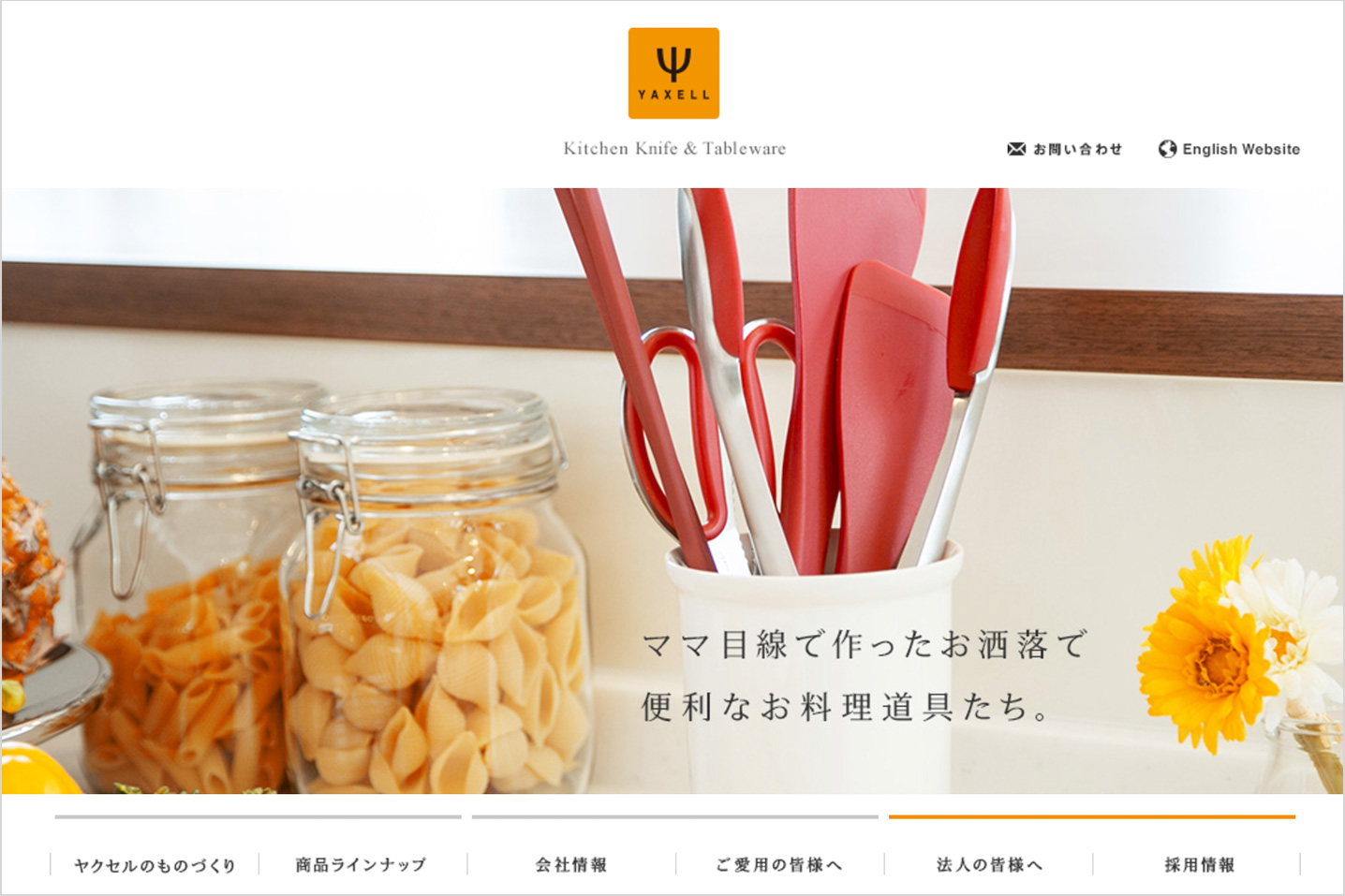
TP明朝は、次世代の明朝体を目指してデザインされた書体です。ハイ、ミドル、ローの3つのコントラストを持ち、横組みで読みやすく、全角ベタ組みで美しく見えるように設計されています。「ディスプレイでの表示に最適化された明朝体というコンセプトに共感したので、Webデザインというフィールドで、これを使わない手はないなと思いました」と言う大津氏。ハイコントラストとローコントラスト、各6ウエイトの導入を決定しました。
大津氏が手がけたサイトのなかで、「mikketa(ミッケタ)」では、TP明朝のハイコントラストが効果的に使われています。シャープなハイコントラスト、そして、細いウエイトが選ばれたTP明朝は、余り糸などを活かしたデザインプロジェクトである「mikketa」製品のテクスチュアとシンクロし、空間に心地よい緊張感をもたらしています。「実はこのサイトのなかで、TP明朝は1箇所しか使っていません。にもかかわらず、そこに存在するだけで、サイトのイメージが変わってくる、そういう強さがこの書体にはあると思います」
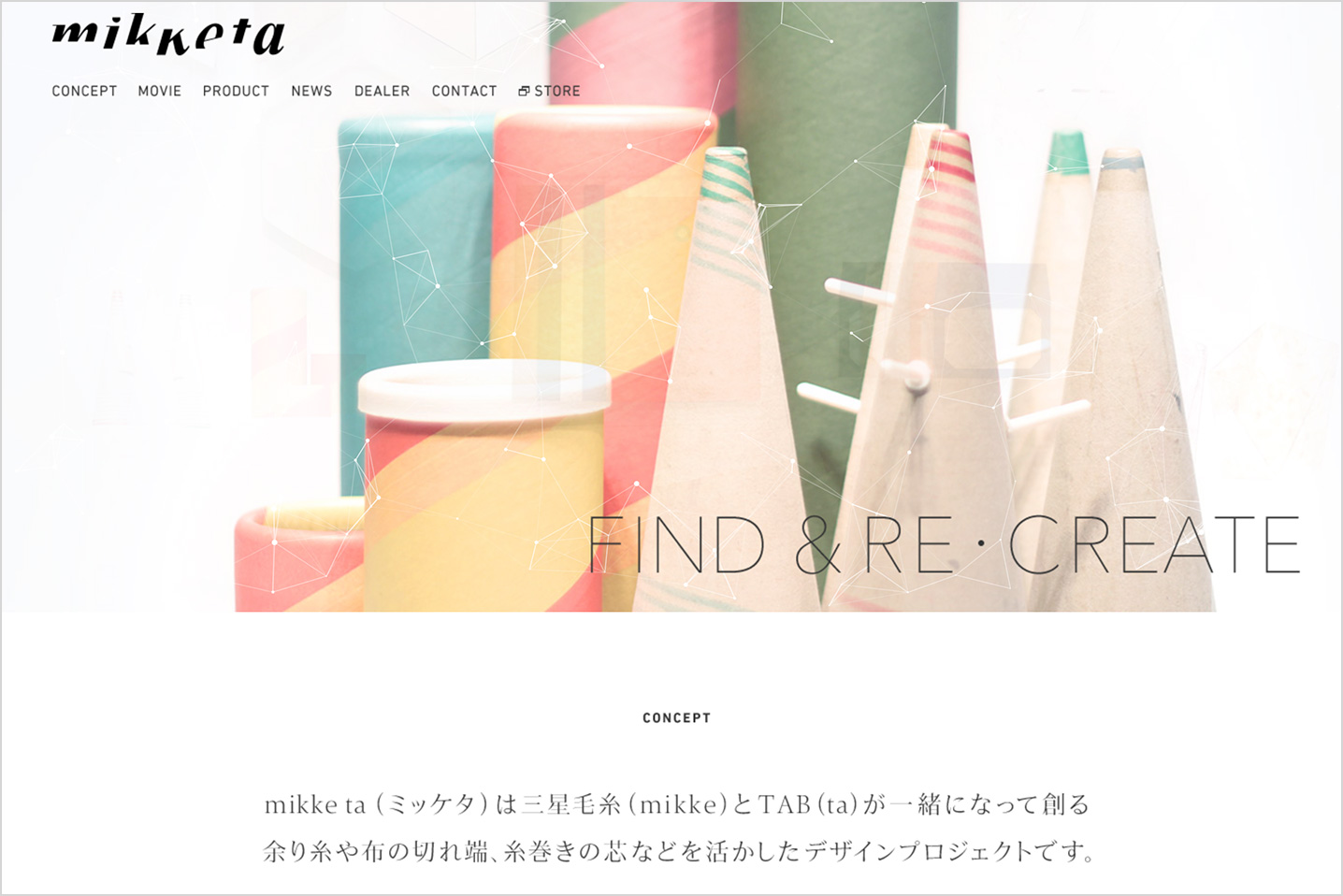
一方、「渡邊万洋税理士事務所」「一宮西病院研修医募集」「株式会社ヤクセル」などのサイトでは、ローコントラストが選ばれました。「Webデザインで明朝体を使用するときは、しばしばアンチエイリアスの調整が必要となります。それに時間がかかったり、希望する印象にならない場合もあるのですが、TP明朝はウエイトが揃っていてコントラストの選択肢もあるので調整の過程でイメージがブレるようなこともありません。特にローコントラストは可読性が高く、Webで使い勝手のいいフォントです。落ち着いた表情なので、信頼感、清潔感を求められるシーンにぴったり合います」
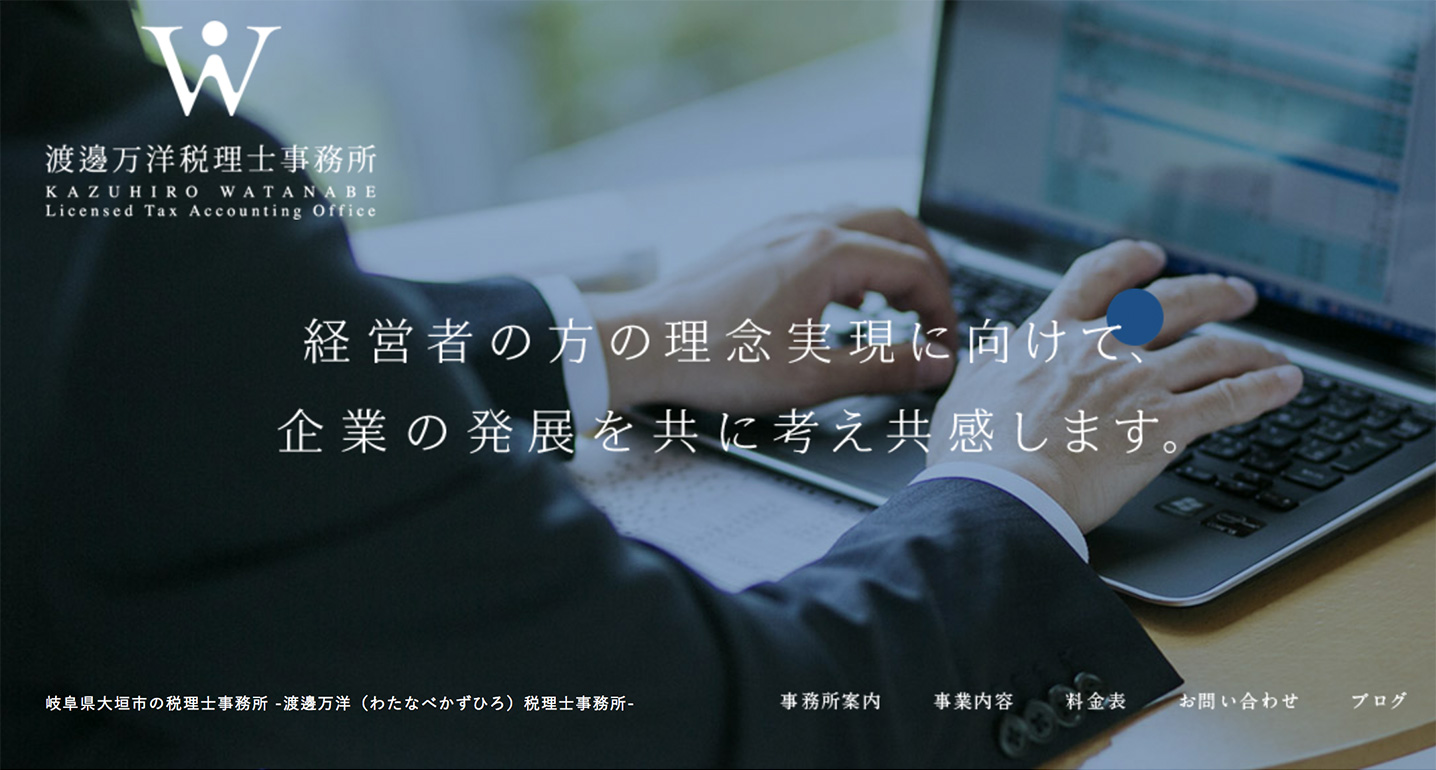
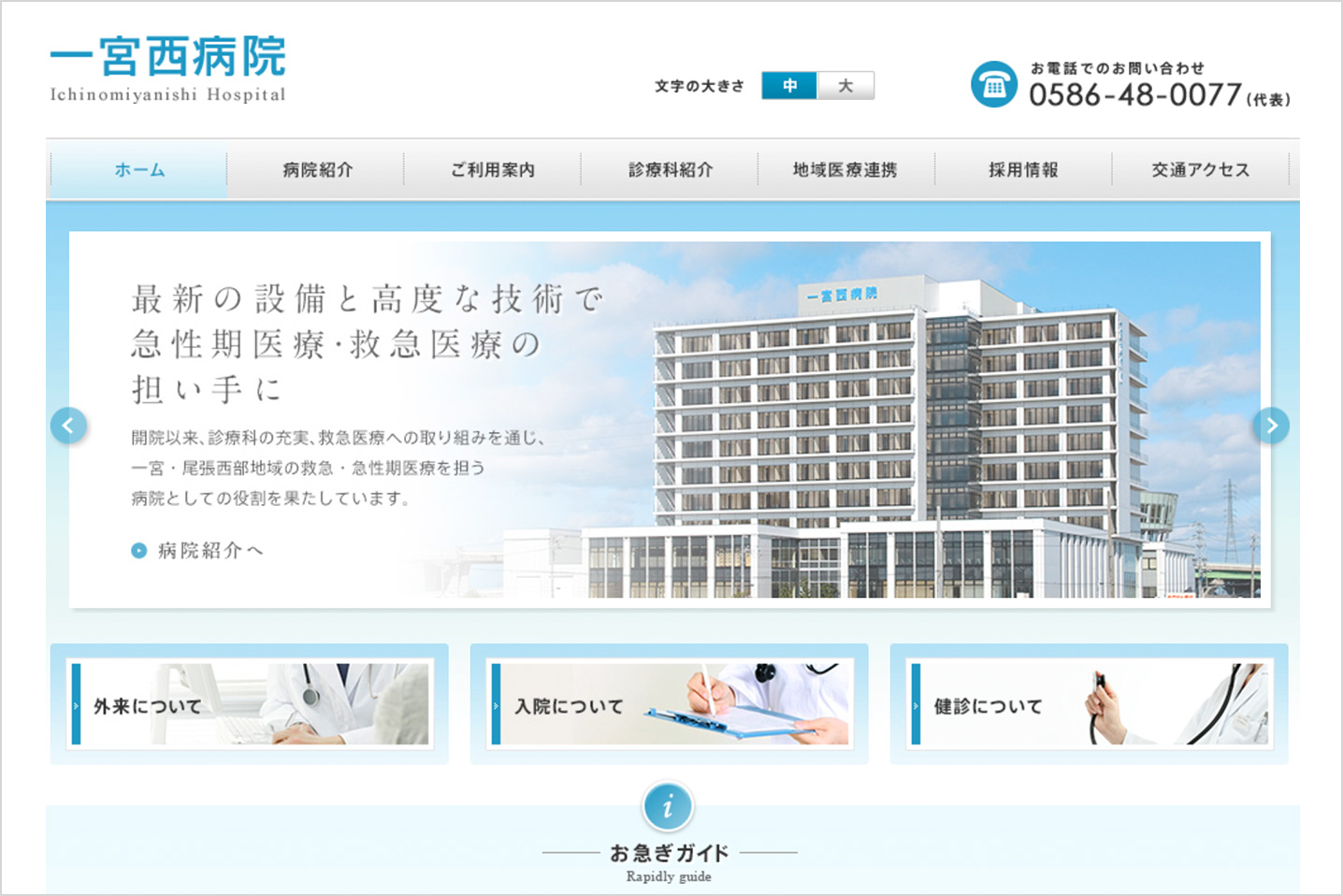
「AXIS FontもTP明朝も好きで、さまざまな場所で使っています。デザイナーとしては珍しいと思うのですが、フォントは年間契約のライセンスではなく、自分が好きなものを購入して使いたいというスタンスでやっているので、タイププロジェクトには、また欲しくなるような素敵なフォントを出してほしいですね。AXIS Fontとは違う欧文フォントを見てみたい気もします。」